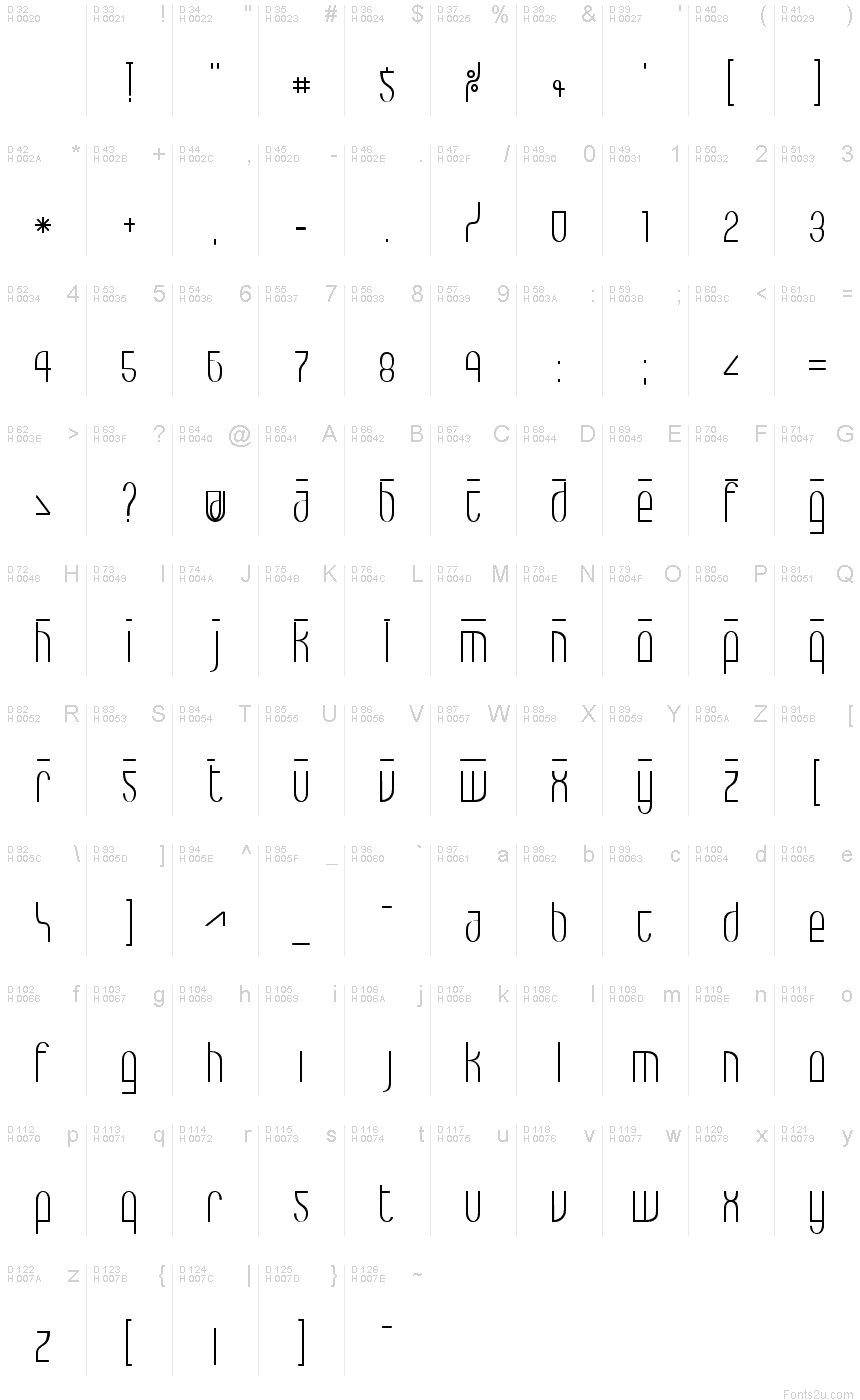
Max von Keith Bates ist eine kostenlose Art-Nouveau-Display-Schrift mit langen, grazilen Strichen und einer ausgesprochen plakathaften Eleganz. Die Buchstaben bestechen durch ihre hohen Vertikalen, haarlinienfeinen Kurven und geschwungenen Verbindungen, die der Schrift einen dekorativen Rhythmus verleihen, ohne ihre moderne Ausgewogenheit zu verlieren.
Sie eignet sich perfekt für redaktionelle Headlines, Fashion-Branding, Buchtitel, Titelkarten oder Verpackungen von Cafés und Boutiquen, bei denen ein Hauch von Glamour den richtigen Akzent setzt. Da Max eine kostenlose Schrift ist, kommt sie am besten in kurzen Texten wie Namen, Cover-Lines oder monogrammartigen Wortmarken zur Geltung, da ihre gestreckten, geschwungenen Formen genügend Raum brauchen, um ihren Charakter voll zu entfalten.